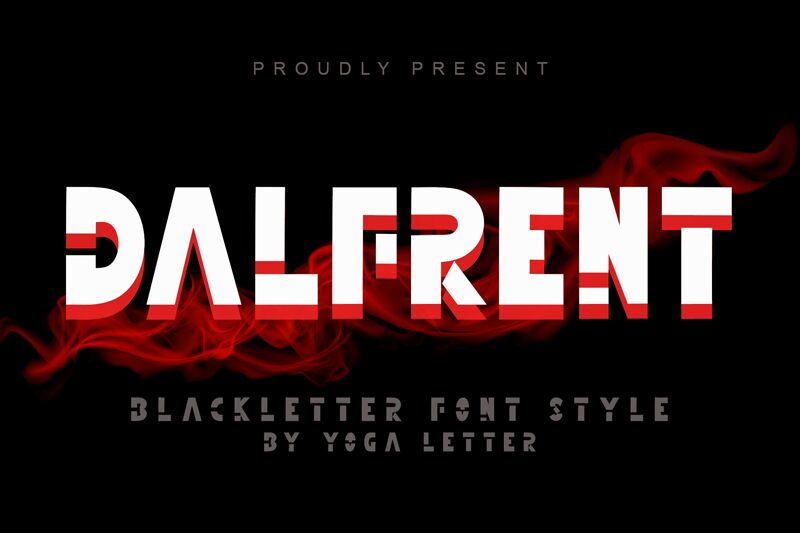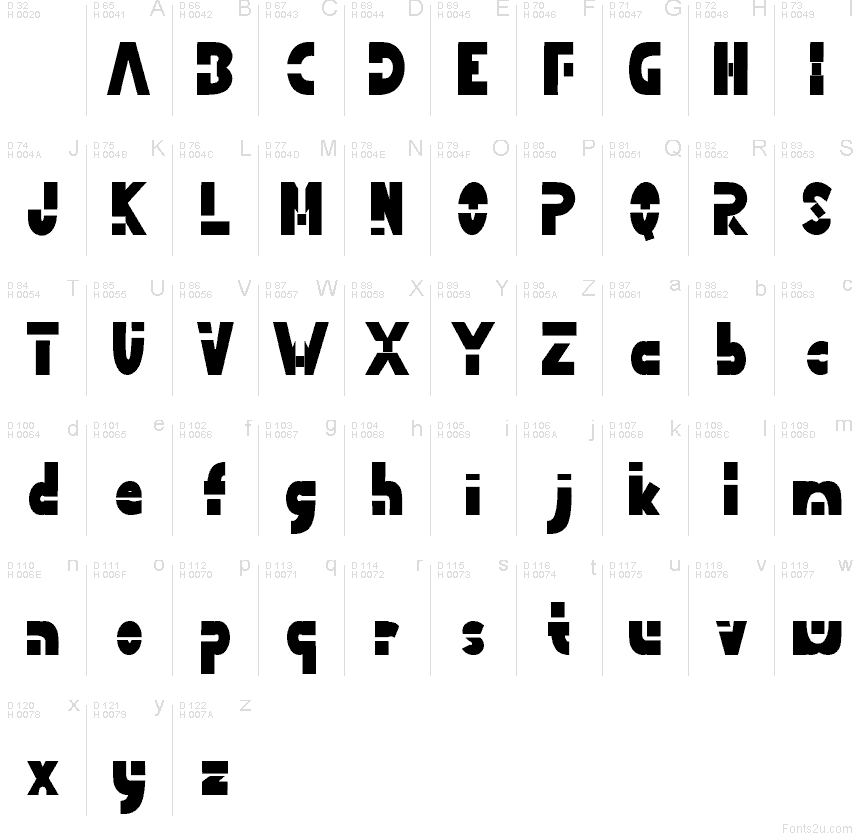
Dalfrent Demo
Dalfrent de Yoga Letter es una tipografía display gratuita con formas redondeadas extragrandes, cortes en bloque cuadrados y detalles de muescas precisas que le confieren una presencia robusta, ideal para cartelería. Sus formas parecen construidas a partir de piezas geométricas sencillas, donde las curvas suaves se ven interrumpidas por bordes rectos y cortes afilados.
Dalfrent funciona muy bien en logotipos, pósteres de eventos, gráficos de videojuegos, títulos, packaging y líneas de branding que requieran una silueta gráfica potente. Esta fuente gratuita aporta la estructura necesaria para titulares impactantes, manteniendo a la vez un ritmo peculiar que da vida a etiquetas decorativas, gráficos para redes sociales y acentos editoriales.